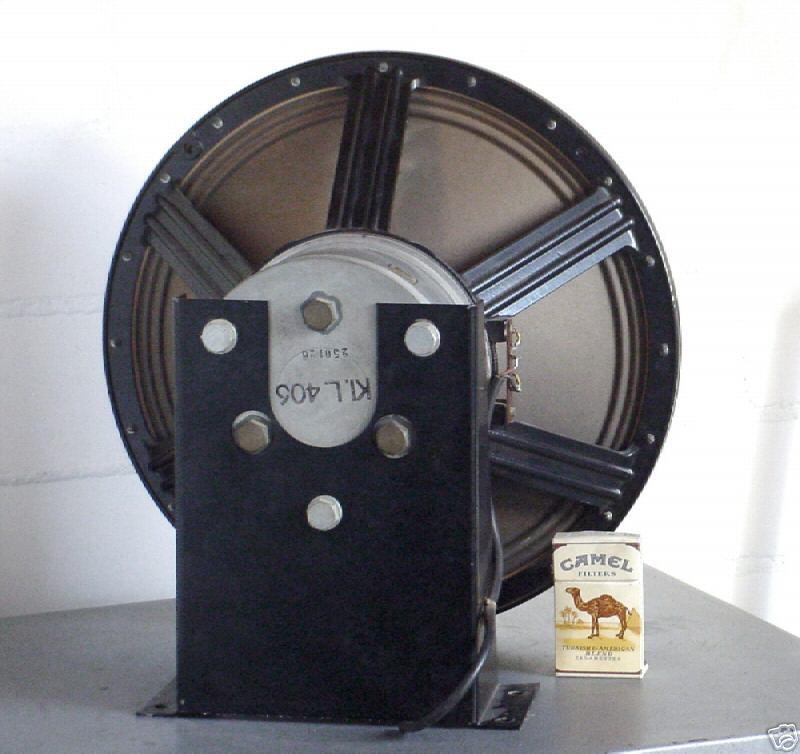
Schriftart erkennen an nur drei Buchstaben und drei Ziffern ?
Guten Abend allerseits. Abgebildet ist ein Stempelbild "Kl. L406" der Firma Siemens aus den 50er Jahren.
Weitere Beispiele habe ich leider nicht.
Was mag das für eine Schrift sein ? Die ulkige Seriennummer sieht aus wie von einem Nummernstempel..
Danke. Handelt es sich bei "Kl. L406" um eine einfache Normschrift ?
Ich sage, es ist keine Normschrift. Und eventuell auch gar keine Schrift. Benannte Schriftarten waren früher Druckschriften aus Blei für den Druck auf Papier. Alle andere Beschriftungen, wie hier auf Metall, wurden anders hergestellt. Von Zeichnungen, im Unternehmen selbstgemachten Schablonen, Stempeln usw. Die Chance ist also gering, eine genau passende Schriftart zu finden. Zumal die Vorlage nicht viel hergibt, sowohl von der Auflösung her als auch den abgebildeten Zeichen. Die sind nicht sonderlich charakteristisch.
Was ist denn überhaupt das Ziel? Wenn es um eine Restauration geht, wäre es nicht sonderlich schwer, die Zeichen von einer besseren Vorlage nachzuzeichnen.
Die 4 ist bei allen damaligen Normschriften offen, daher würde ich ebenfalls eine Normschrift ausschließen. Die Glyphenform hat sich bei Stempeln damals eher nach praktischen Gesichtspunkten gerichtet, da standen Haltbarkeit, Eindeutigkeit, geringe Verschmutzung im Vordergrund. Gestaltet wurden die Glyphen damals meist von Hand, natürlich beeinflusst von bestehenden Schriften.
Es handelt sich um einen Stempel, soweit richtig.
Das motiviert jedenfalls alles nicht gerade, weiter Hilfe für deine Typografie-Fragen zu geben.
Den Ordnungsruf nehme ich zu Kenntnis, bin aber nicht sicher, ob er mich betrifft.
In sprachlichen Angelegenheiten bin ich gelegentlich empfindlich. Mein anfängcher kleiner Einwand, humoristisch duch das angefügte "prost", musste freilich keine Belehrungskaskade auslösen.
Mit "Buttons" und so kenne ich mich nicht aus.
Der Duden, ein Erzeugnis privater Verleger, ist kein Regelwerk, sondern eine Bestandsaufnahme der deutschen Sprache - und das überwiegend auch ohne die schweizer und österreichische Sicht. Da kann man indessen bestimmt das Gendern erlernen.
Danke für den Hinweis auf den "Restaurator Hub", der hat jedoch auf seiner eigentlichen Firmenpräzenz https://www.restaurator-hub.de/ alles richtig gemacht.
vor 3 Stunden schrieb ASB:
alles richtig gemacht.
Da bin ich ja froh, dass du deinen Fehler eingesehen hast.
Noch ein anderes Beispiel:
Nur weil der Begriff selten verwendet wird, heißt das nicht, dass er falsch ist.
vor 7 Stunden schrieb Ralf Herrmann:
Nach Prüfung der Quellen, stimme ich dem nun auch zu
Die Quellen geben aber nicht her, dass die Arbeit an Kunstwerken nur Restaurierung heißt. So schreibt auch das DWDS:
2Restauration, die
[österreichisch] Gaststätte
https://www.dwds.de/wb/Restauration